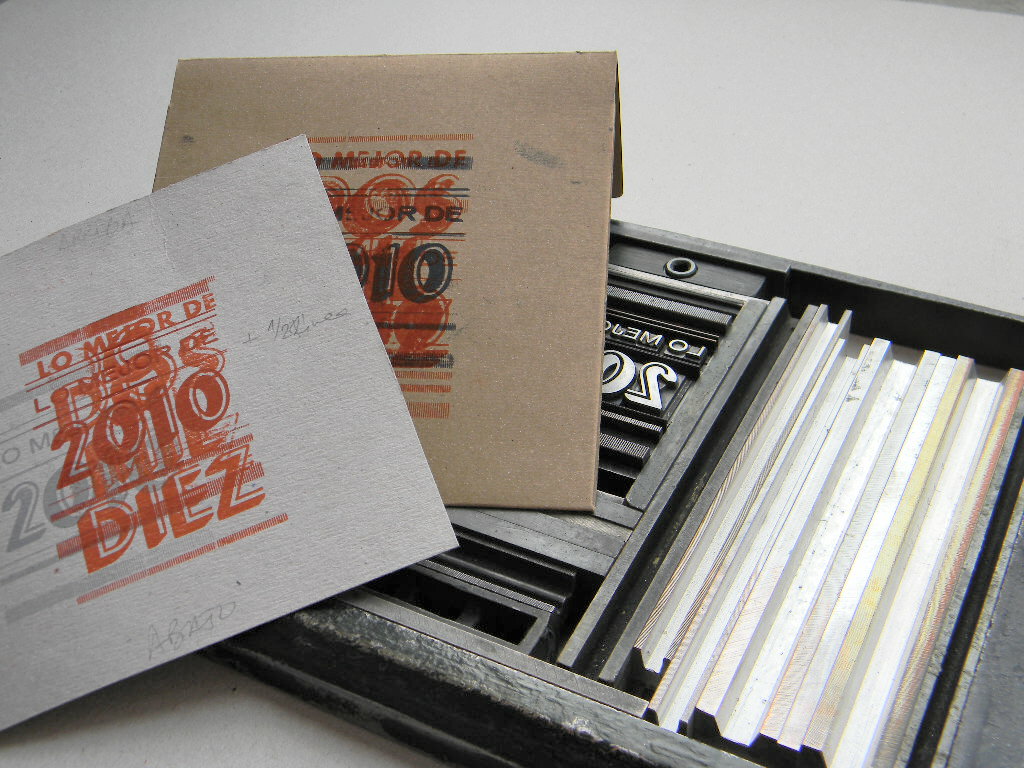
Muy cerca de Valencia, en 25 m2, Lola ha montado un pequeño taller de tipografía. Con una minerva Barcino, tres chibaletes y una guillotina imprime tarjetería como se hacía antes. Casualmente, la mayoría de las cajas de tipos que ha podido recolectar son de tipografía Futura así que era inevitable que el logo de su marca, Oficio, también fuera en esta tipografía.
Además de las cajas de Futura, casi todas de cuerpos grandes, también han caído en sus manos varias cajas con tipografía Venus, con Bodoni, y, entre otros, el interesante tipo Greco, que Carl Winkow diseñó durante su etapa madrileña para la fundición de Richard Gans.
Alfredo Lazo (impresor de Godella) ha estado enseñando a Lola los oficios de la imprenta (tipógrafo, cajista y maquinista) durante 5 años, siempre con minervas de alimentación manual. Ahora le toca enfrentarse a la Heidelberg de aspas.